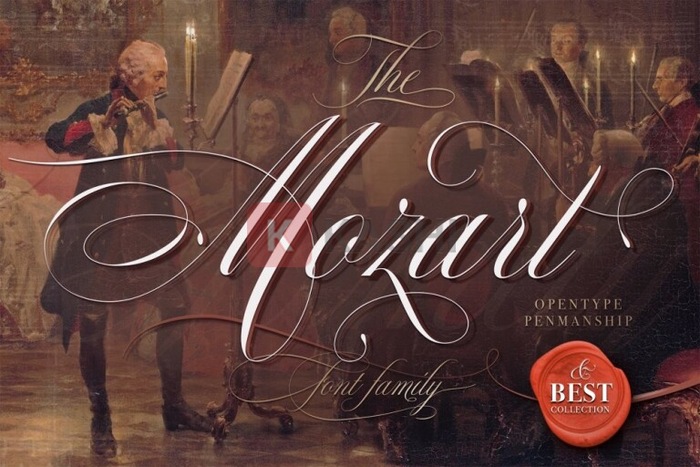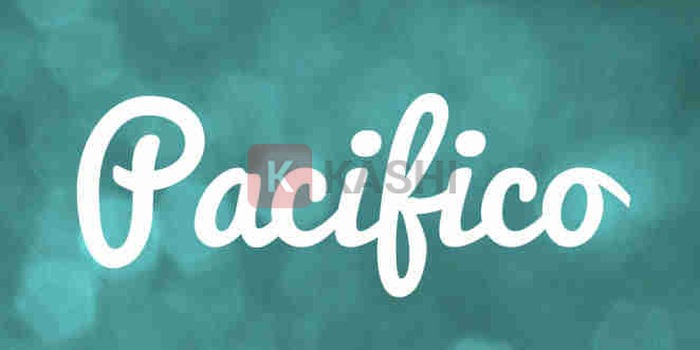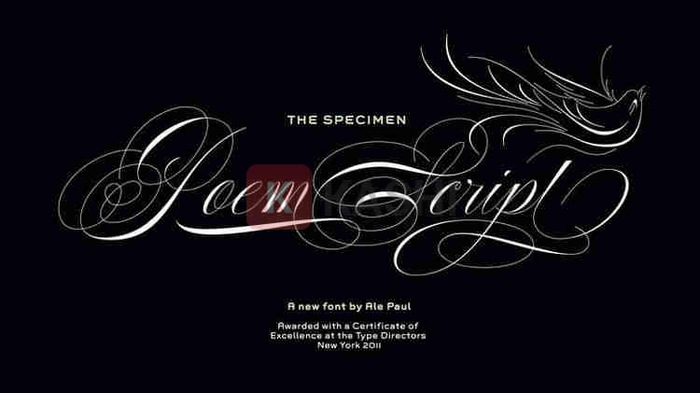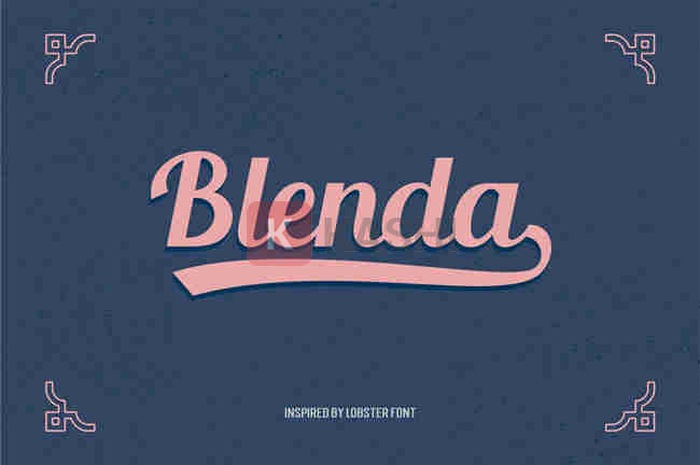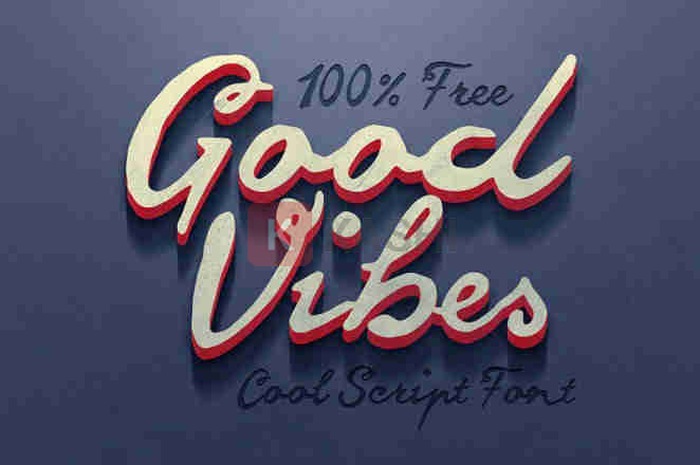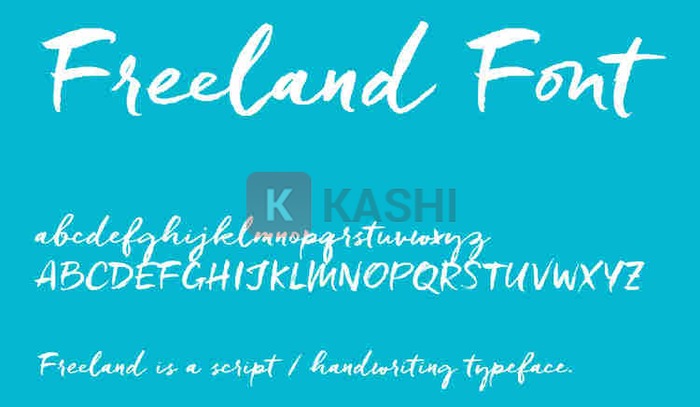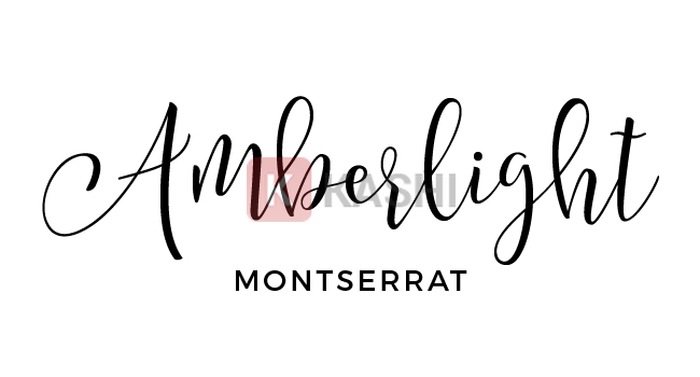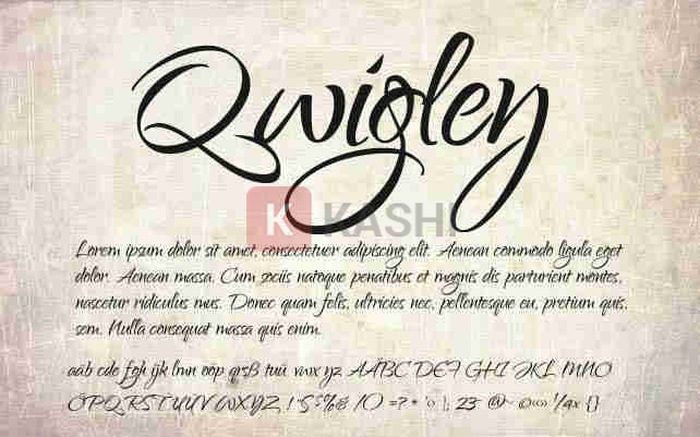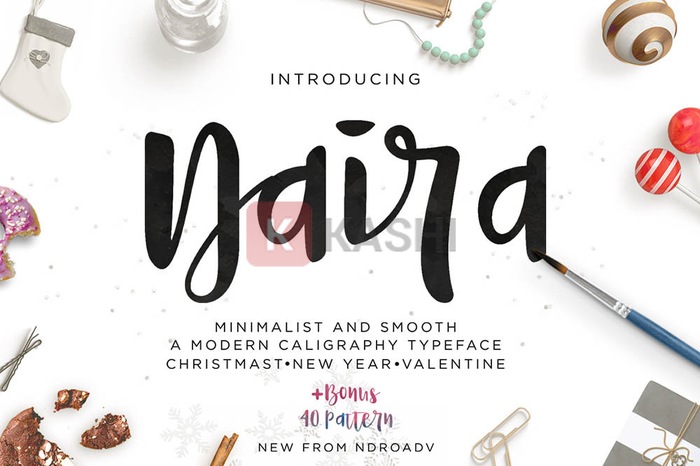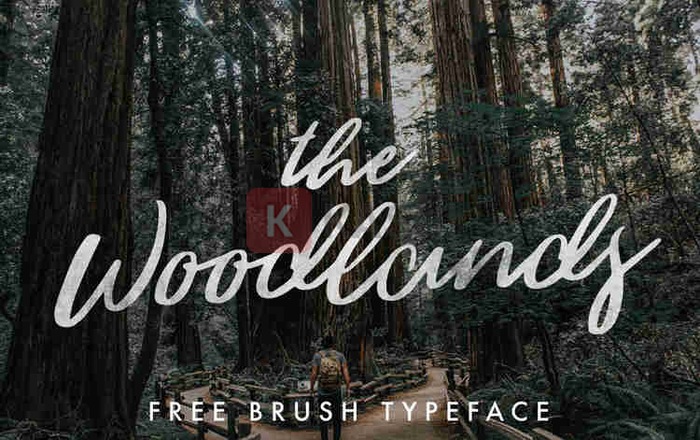
20+ Font Chữ Calligraphy Việt Hóa Tuyệt Đẹp 2025
Bạn đang tìm kiếm font chữ calligraphy đẹp để thiết kế thiệp, logo, hoặc các sản phẩm đồ họa nghệ thuật? Bài viết này sẽ giới thiệu bộ sưu tập hơn 20 font chữ calligraphy Việt hóa miễn phí, đa dạng phong cách, giúp bạn tạo nên những tác phẩm ấn tượng. Tải về và sử dụng ngay hôm nay!
Font Chữ Calligraphy là gì?
Font chữ calligraphy là kiểu chữ viết tay, mang nét đẹp hoa mỹ, lộng lẫy và sang trọng. Nó mang hơi thở cổ điển, tạo nên sự tao nhã, quyến rũ và một chút hoài cổ cho thiết kế. Được viết bằng cọ hoặc bút có ngòi đặc biệt, font calligraphy sở hữu những đường nét mềm mại, thanh thoát, làm nổi bật vẻ sang trọng trong bất kỳ tác phẩm nào.
Calligraphy (nghệ thuật thư pháp hiện đại) bắt nguồn từ tiếng Hy Lạp cổ đại, kết hợp từ “kallos” (κάλλος) – “vẻ đẹp” và “graphex” (γραφή) – “văn bản”. Calligraphy là nghệ thuật tôn vinh vẻ đẹp của chữ viết, nơi các nét chữ được kết hợp hài hòa và tinh xảo.
Font chữ Calligraphy
Khi nào nên sử dụng Font Chữ Calligraphy?
Với vẻ đẹp lộng lẫy và sang trọng, font chữ calligraphy thường được dùng trong thiệp mời, thiệp chúc mừng, poster, logo, hoặc các sản phẩm đồ họa nghệ thuật chú trọng sự tinh tế và mềm mại. Font calligraphy Việt hóa phù hợp để trang trí hơn là dùng cho văn bản dài, vì có thể gây khó đọc. Sử dụng font calligraphy cho tiêu đề và đề mục sẽ là lựa chọn hợp lý hơn.
Bộ Sưu Tập 20+ Font Chữ Calligraphy Việt Hóa 2025
Dưới đây là tuyển tập những font chữ calligraphy đẹp và ấn tượng, với nhiều phong cách đa dạng, giúp bạn thỏa sức sáng tạo.
1. Font Aphrodite Slim
Được thiết kế bởi Maximiliano Sproviero, Sabrina Mariela Lopez và Aphrodite Slim, font chữ này là sự kết hợp của hơn 1000 đường cong mềm mại, mang đến vẻ đẹp trang trọng, thường được ưa chuộng trong lĩnh vực in ấn.
2. Font Qwigley Regular
Font chữ brush tuyệt đẹp này đã từng đoạt giải thưởng thiết kế đương đại với phong cách cách điệu độc đáo.
3. Font Allura
Được thiết kế bởi Rob Leuschke, Allura là font chữ calligraphy theo định dạng Allura Pro, mang tính cách điệu nhưng vẫn dễ đọc.
4. Font Freeland
Font chữ viết tay mang phong cách vintage này được tạo nên từ những nét brush in đậm, hiện đại, kết hợp chữ ghép và chữ thường độc đáo.
5. Font Learning Curve Pro
Đây là kiểu font chữ viết tay mang nét đẹp truyền thống.
6. Font Dancing Script
Font chữ “nhảy” này có kích thước chữ thay đổi linh hoạt trên và dưới đường cơ sở, tạo nên sự sinh động.
7. Font Good Vibes
Với những đường nét uyển chuyển, dễ đọc, Good Vibes tạo ấn tượng thú vị ngay từ cái nhìn đầu tiên.
8. Font Cursif
Cursif là kiểu chữ với nét thanh nét đậm, mô phỏng nét bút viết tay, tạo nên vẻ đẹp trang trọng.